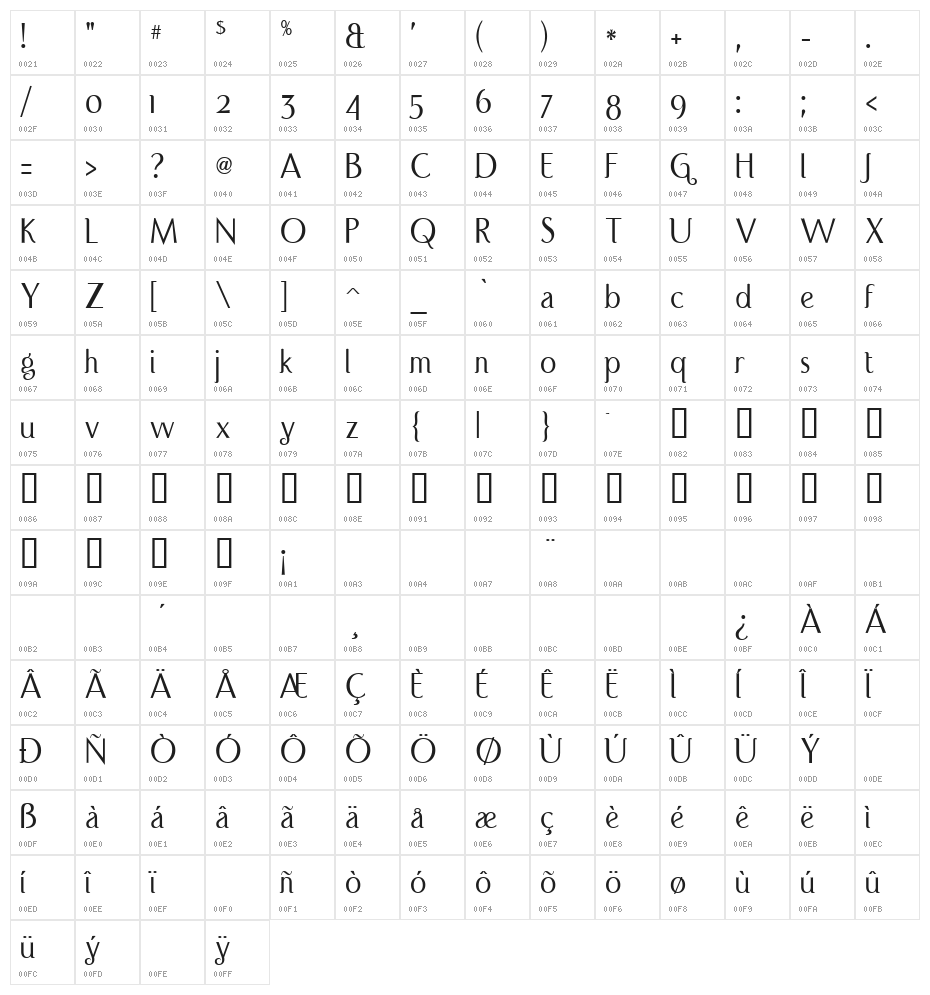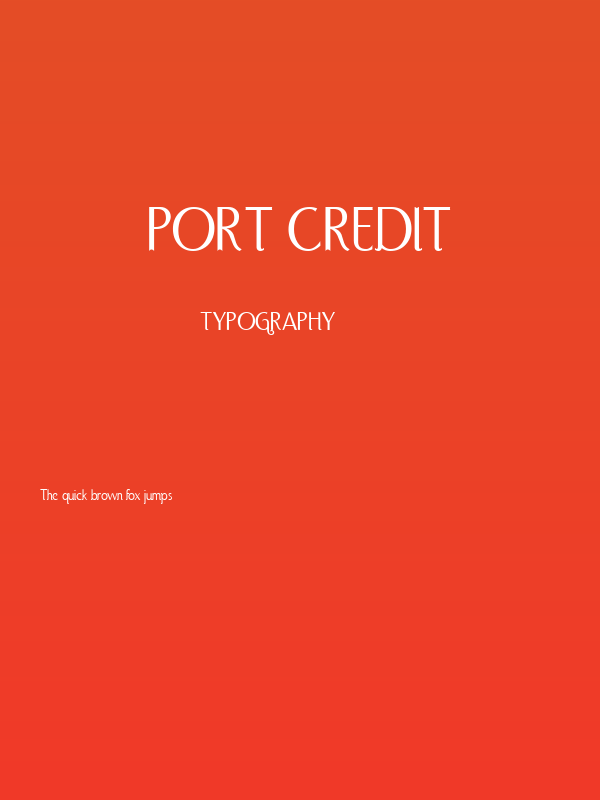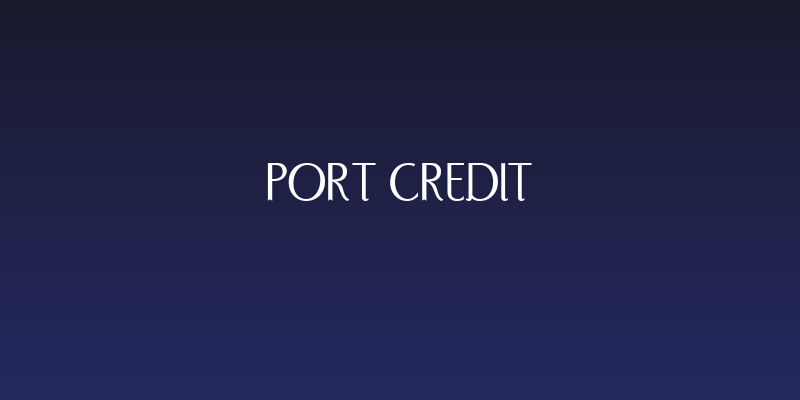
Port Credit Font
✎ Serif
| Stile generale | Elegant and modern |
| Caso d'uso | Headlines, Logos, Invitations |
| Progetti proposti | Ideal for branding, editorial design, invitations, and luxury product packaging. |